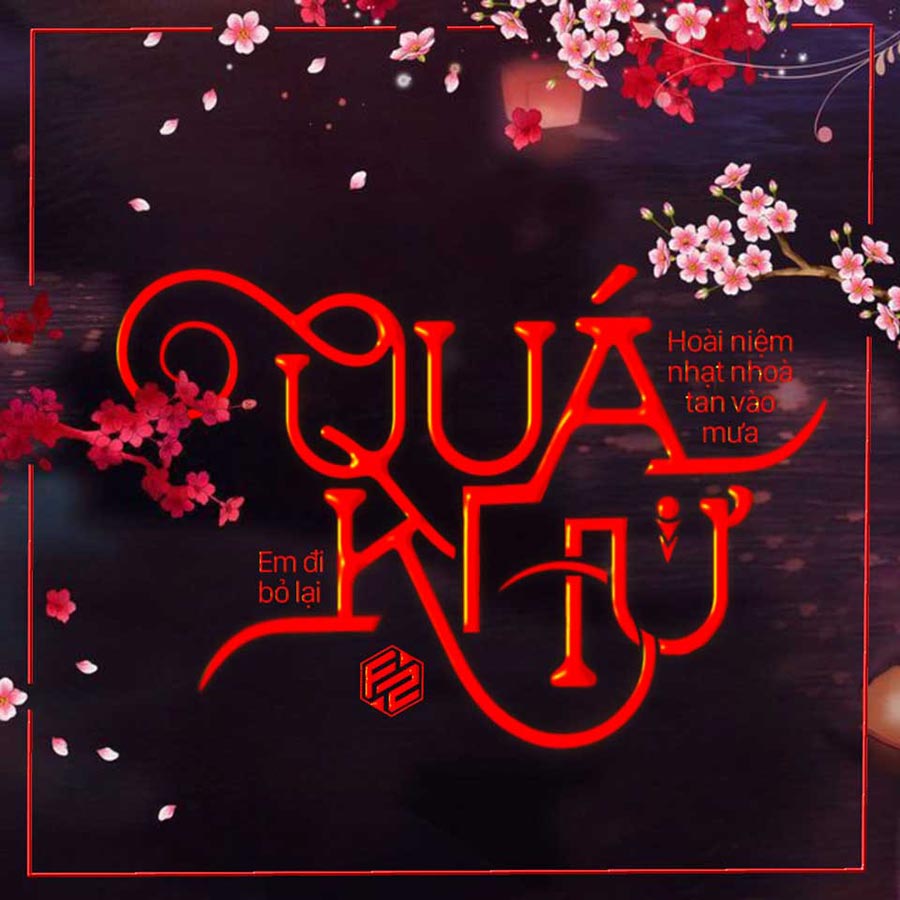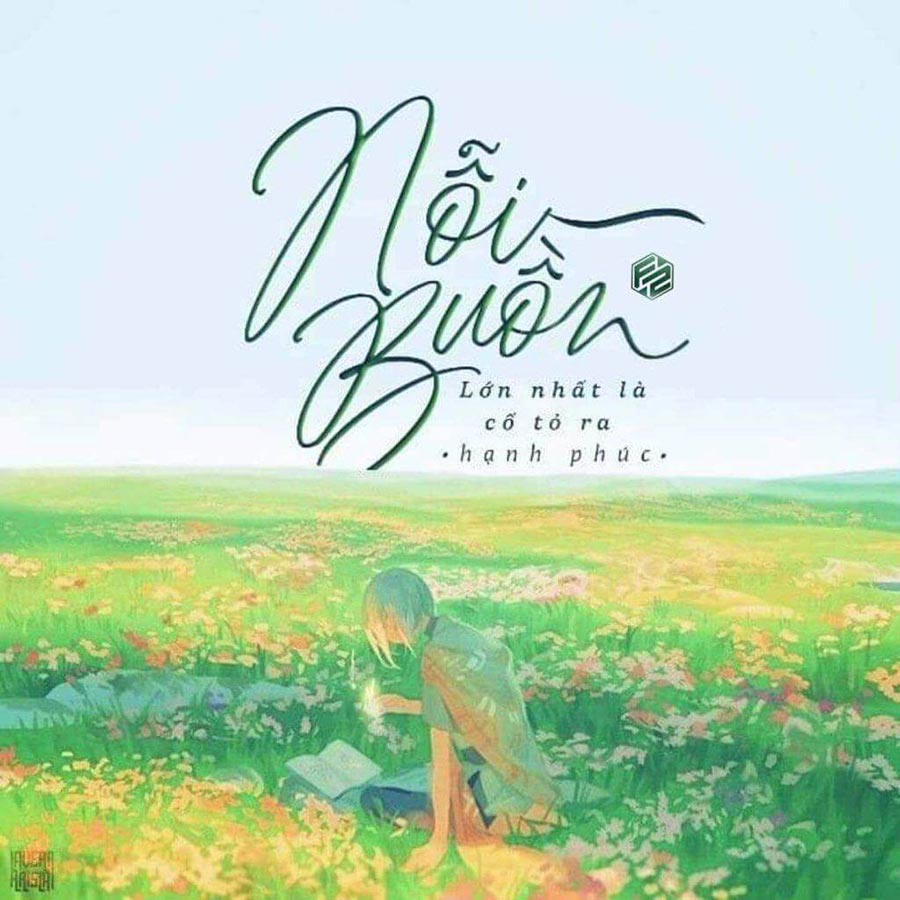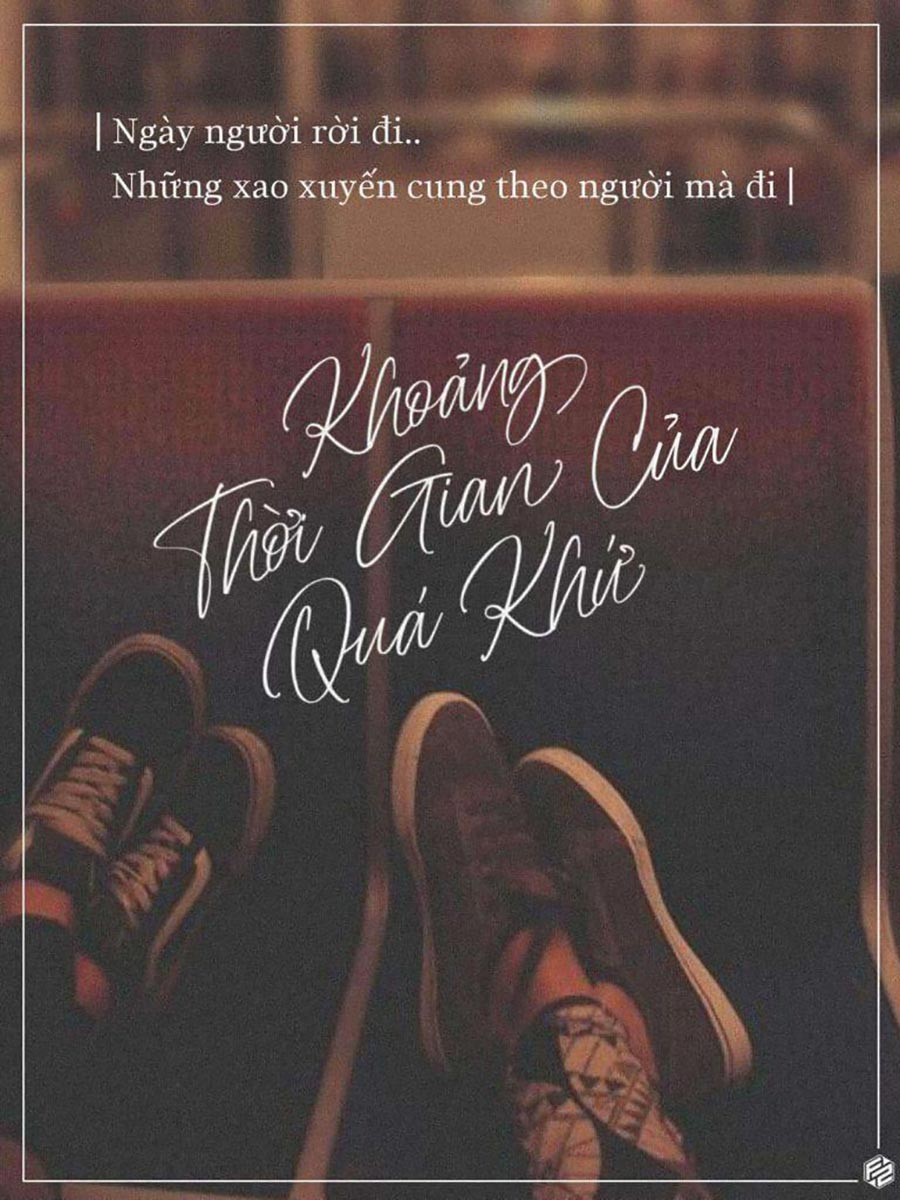
Chia Sẻ Miễn Phí 2 Font Abu Dhabi Và The Wild Hammer Phong Cách Vintage
Nếu bạn đang tìm kiếm những font chữ phong cách vintage để nâng cao chất lượng thiết kế của mình, thì Abu Dhabi và The Wild Hammer chính là lựa chọn tuyệt vời. Được thiết kế với sự tinh tế và đầy cá tính, hai font chữ này sẽ mang đến một làn gió mới cho những dự án sáng tạo của bạn. Hôm nay, chúng tôi chia sẻ miễn phí cả hai font này, giúp bạn tiết kiệm chi phí mà vẫn sở hữu những font chất lượng cao.
Đặc Điểm Nổi Bật Của Font Abu Dhabi
Font Abu Dhabi mang đậm phong cách cổ điển với những đường nét mềm mại, tinh tế nhưng không kém phần hiện đại. Với thiết kế tỉ mỉ, font này rất phù hợp cho các dự án cần sự sang trọng, thanh thoát, chẳng hạn như thiết kế logo, thiệp cưới, hoặc các ấn phẩm in ấn cao cấp. Font Abu Dhabi mang lại cảm giác của một thời đại đã qua, nhưng vẫn đủ sức cuốn hút trong mọi không gian thiết kế hiện đại.
Ứng Dụng Của Font Abu Dhabi
Font Abu Dhabi rất lý tưởng cho những ai yêu thích sự nhẹ nhàng, tinh tế nhưng không kém phần mạnh mẽ. Bạn có thể sử dụng font này trong thiết kế quảng cáo, tên thương hiệu, hoặc các tiêu đề của bài viết, website để tạo nên sự ấn tượng mạnh mẽ và dễ dàng thu hút sự chú ý của người xem.
Đặc Điểm Nổi Bật Của Font The Wild Hammer
Font The Wild Hammer mang đến một phong cách vintage mạnh mẽ, với những đường nét sắc sảo và hơi "hoang dã". Đây là font chữ lý tưởng cho những dự án đậm tính cá nhân, sáng tạo và nổi bật. Được thiết kế với sự kết hợp giữa cổ điển và phóng khoáng, The Wild Hammer sẽ giúp bạn tạo ra những thiết kế đầy ấn tượng, khác biệt hoàn toàn so với những font chữ thông thường.
Ứng Dụng Của Font The Wild Hammer
Nếu bạn muốn tạo ra một thiết kế có cá tính mạnh mẽ, độc đáo và đầy ấn tượng, font The Wild Hammer sẽ là sự lựa chọn tuyệt vời. Font này rất phù hợp với các thiết kế poster, banner, logo cho các thương hiệu trẻ trung, đầy năng lượng hoặc các dự án cần sự nổi bật, phá cách.
Abu Dhabi và The Wild Hammer là hai font chữ vintage tuyệt vời, mang lại sự sáng tạo và cá tính cho các dự án thiết kế của bạn. Việc sử dụng chúng sẽ giúp bạn dễ dàng tạo ra những sản phẩm độc đáo, thu hút mọi ánh nhìn. Hãy tải miễn phí hai font chữ này ngay hôm nay và áp dụng vào các thiết kế của bạn để tạo nên những tác phẩm đầy ấn tượng!